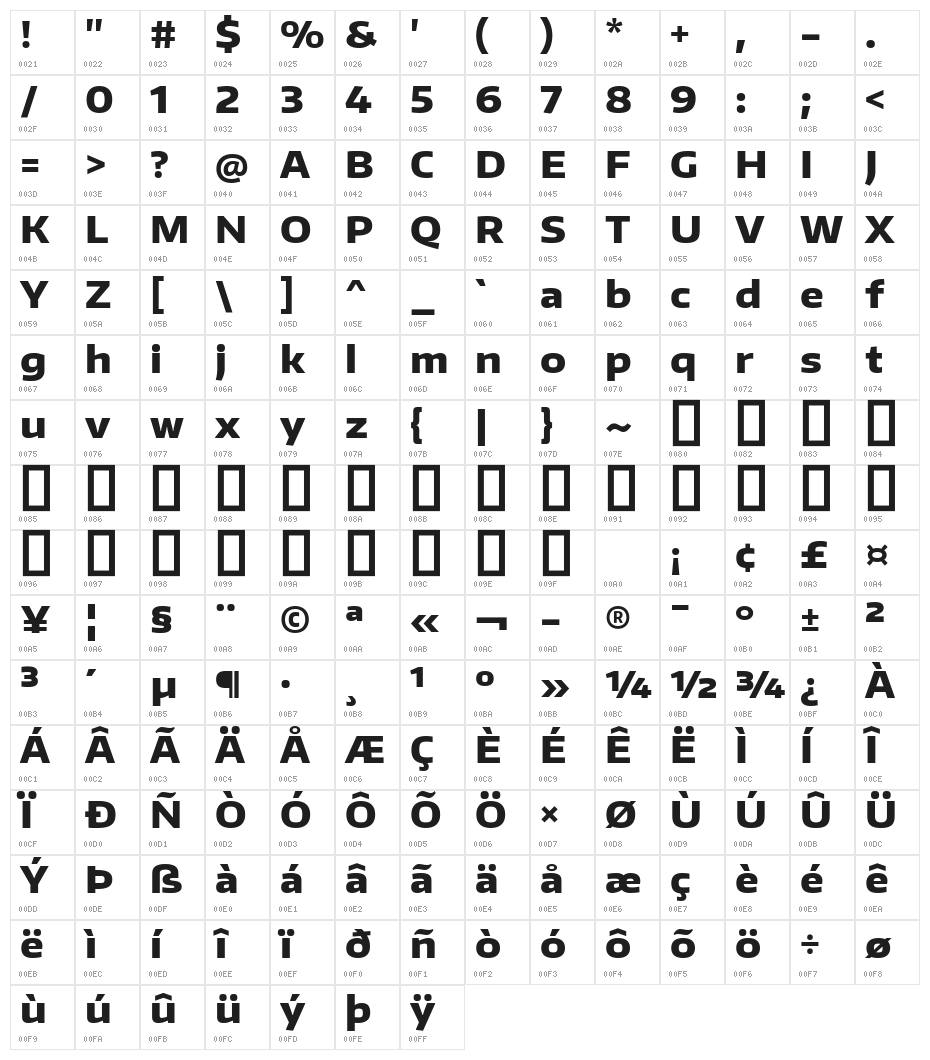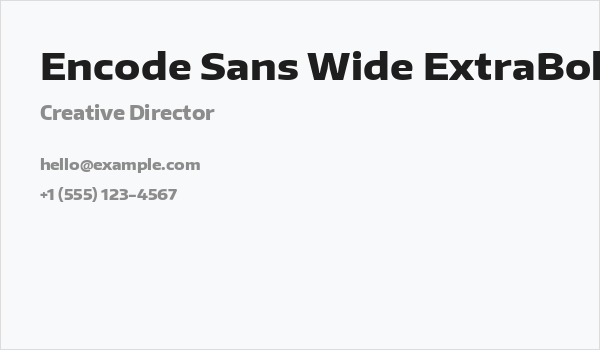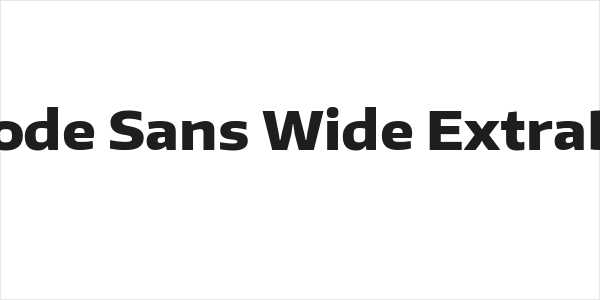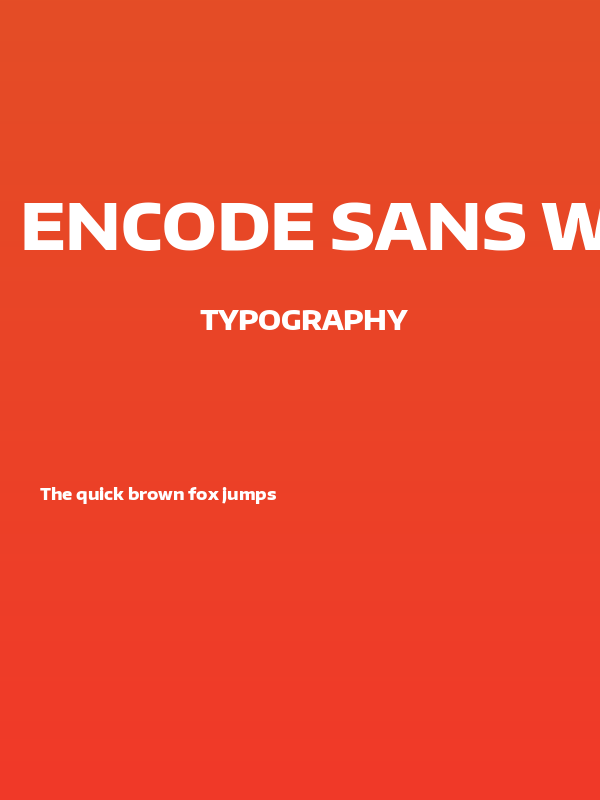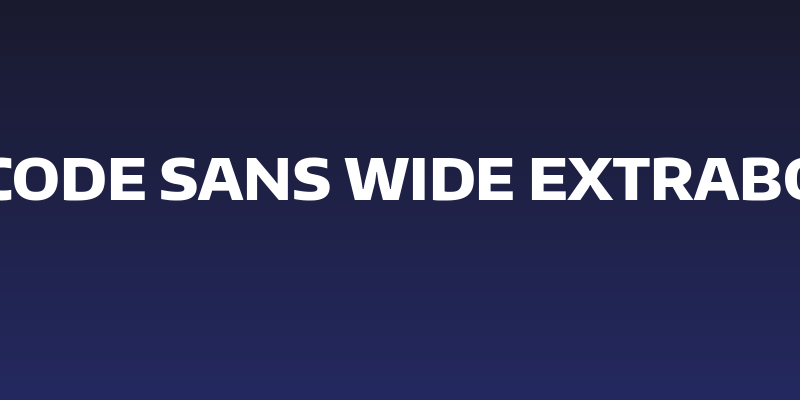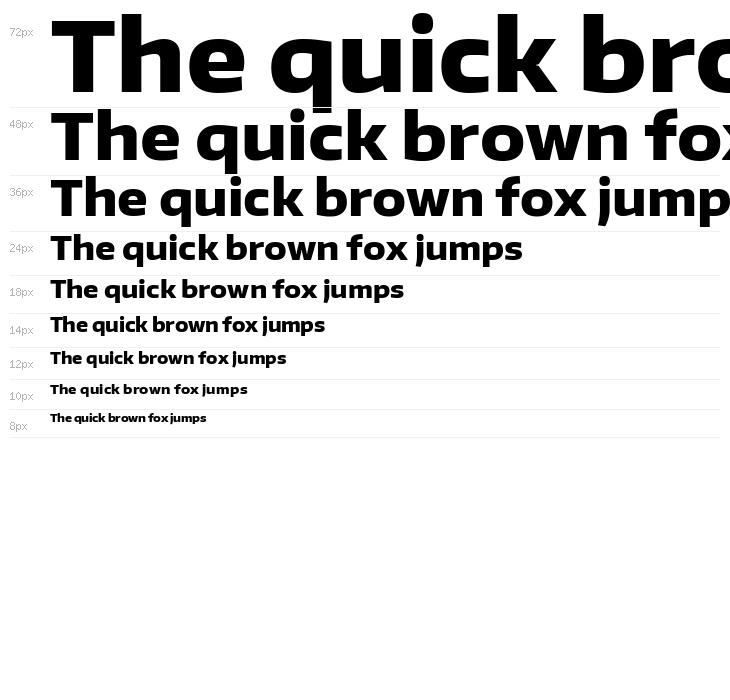
Encode Sans Wide ExtraBold Font
| Larghezza | Expanded |
| Progetti proposti | Ideal for branding, headlines, posters, and digital media where a strong visual impact is desired. |